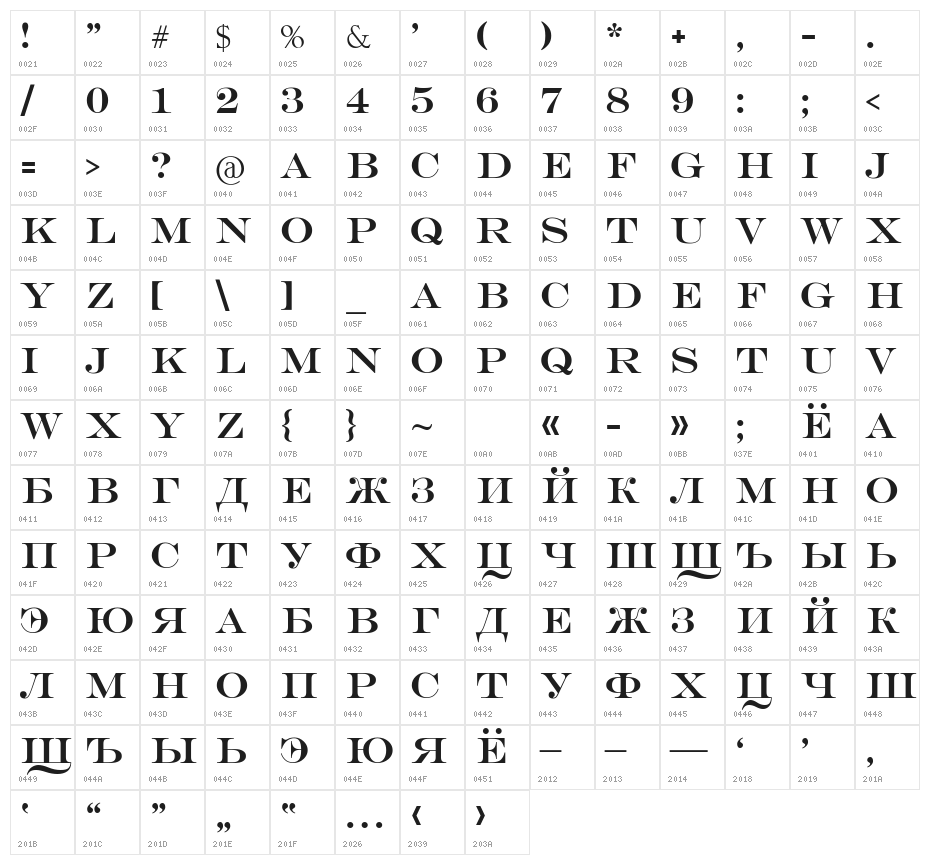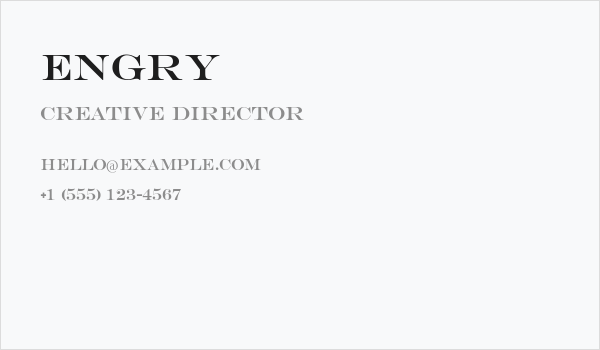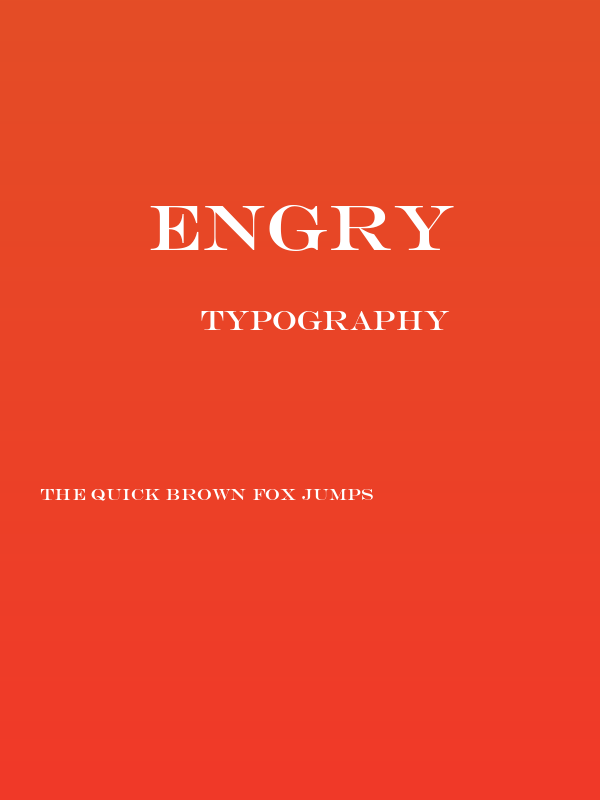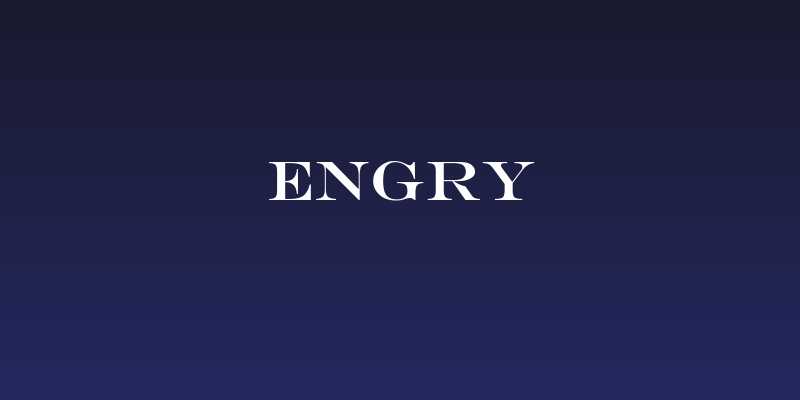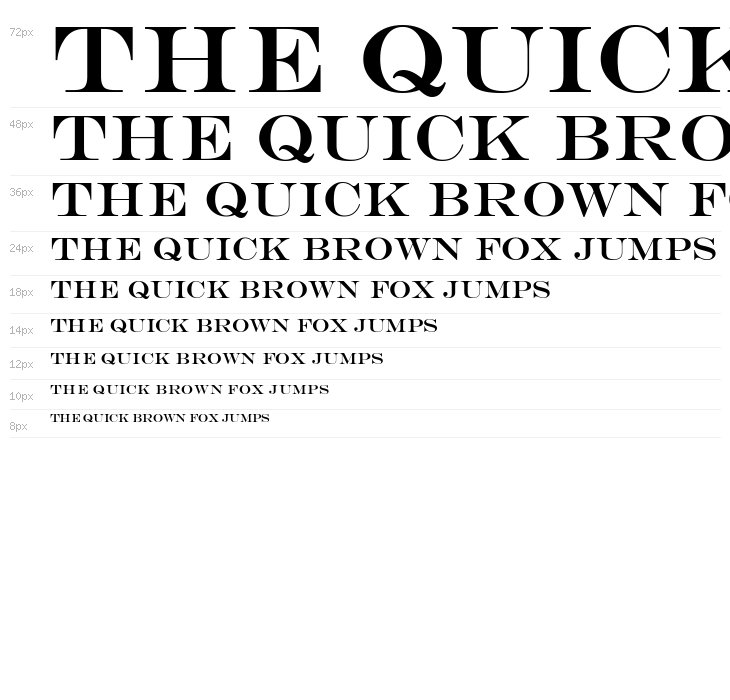
Engry Font
يتضمن هذا الخط 119 حرفًا. انقر على أي حرف لرؤية التفاصيل.
| الفئات | Serif |
| النمط العام | Classic |
| حالة الاستخدام | Headlines, Body text, Logos |
| مشاريع مقترحة | Ideal for editorial design, book covers, formal invitations, and branding projects that require a touch of elegance and tradition. |